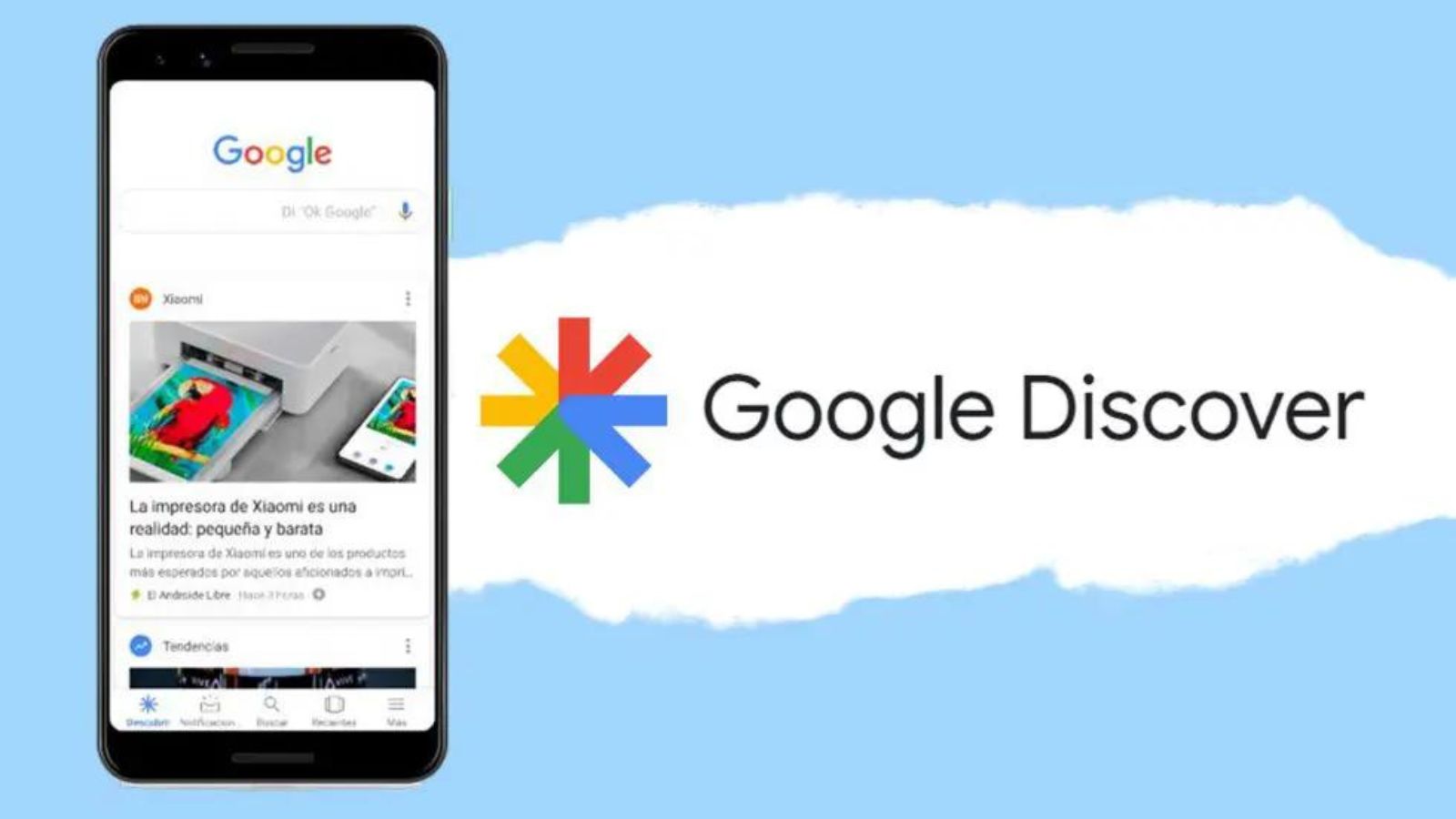
Google Discover, la piattaforma integrata nell’app Google e presente nella schermata a sinistra dei dispositivi Android, introduce alcune modifiche grafiche e funzionali che puntano a migliorare la leggibilità e la trasparenza delle notizie visualizzate. Tra le novità principali si segnala una nuova disposizione del nome del sito, che ora compare sopra il titolo dell’articolo, e un aggiornamento del font per favorire la distinzione dei contenuti.
Riorganizzazione visiva per maggiore chiarezza
Nella nuova versione dell’interfaccia, il nome del sito web che pubblica il contenuto appare nella parte superiore della card, in posizione più visibile rispetto al passato. In precedenza, questa informazione era collocata sotto al titolo, con una formattazione più discreta. Il nuovo layout rende quindi immediatamente chiaro da quale fonte provenga l’articolo, contribuendo a migliorare la trasparenza e la fiducia nel contenuto proposto.
Un altro cambiamento riguarda il font utilizzato nei titoli degli articoli, che ora risulta più marcato e leggibile. Questo intervento migliora la chiarezza del contenuto principale e rende più immediata la comprensione della notizia proposta. L’obiettivo di Google è quello di guidare l’utente verso una lettura più fluida, riducendo le distrazioni e rendendo evidente il contenuto centrale dell’articolo.
Il nuovo font potrebbe rientrare in un aggiornamento più ampio legato al design complessivo dell’interfaccia, in linea con le linee guida Material You già adottate in altri ambiti dell’ecosistema Android.
L’intervento più rilevante rimane però quello sul posizionamento del nome della fonte, che mira a rafforzare la credibilità delle notizie mostrate su Discover. In un periodo in cui la verifica delle informazioni è sempre più cruciale, Google sembra voler rispondere alla crescente esigenza di trasparenza nell’algoritmo di suggerimento dei contenuti.
Mostrare il nome del sito in alto può anche facilitare l’utente nella selezione delle fonti preferite o nell’evitare portali ritenuti meno affidabili. Questo approccio ricalca scelte già viste in altri aggregatori di contenuti o feed di notizie, dove la provenienza dell’informazione è un parametro fondamentale per la fruizione consapevole.
Nonostante gli aggiornamenti grafici, il comportamento di Discover rimane invariato: il feed continua a proporre contenuti personalizzati in base agli interessi dell’utente, alla cronologia di navigazione, alle ricerche effettuate e ad altri segnali contestuali. Il sistema punta quindi a un equilibrio tra personalizzazione e affidabilità delle fonti, rendendo più chiara l’origine di ogni notizia suggerita.
L’interfaccia resta compatibile con tutte le funzionalità preesistenti, incluse le opzioni per nascondere i contenuti indesiderati, seguire determinati temi o regolare la frequenza degli aggiornamenti.